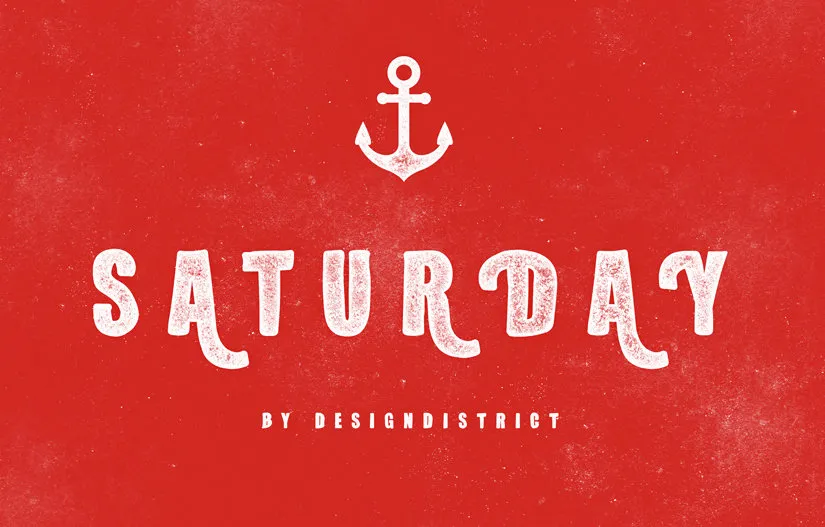
Introduzimos uma nova fonte chamada “Saturday”, com um estilo vintage forte e elegante. Esta tipografia foi projetada para se adequar perfeitamente aos rótulos, tornando-a ideial para qualquer projeto que exija uma aparência vintage, seja ela em cartazes de cinema, capas de álbum ou até mesmo em marcas de espetáculos. “Saturday” é ideal para aqueles momentos especiais onde você deseja transmitir claramente sua mensagem e deixar um impacto visual. Com seu design atraente, essa fonte é perfeita para uso em aplicações que exigem destaque, como rótulos de embalagens, capas de discos ou até mesmo nos legindários créditos finais de filmes. Sem dúvida, o “Saturday Typeface” se torna uma ferramenta indispensável para quem busca um estilo vintage moderno e versátil em seus trabalhos visuais.